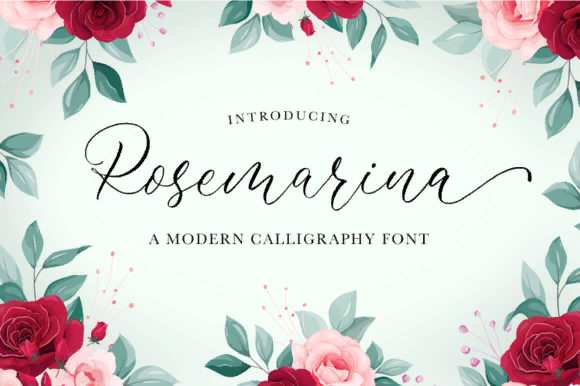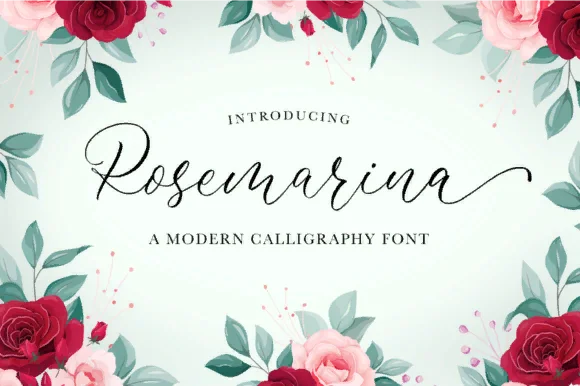
Название: Rosemarina Font (2021)
Rosemarina - это прекрасный и неподвластный времени рукописный шрифт.
Это лучший выбор для создания привлекательных логотипов, брендинга и цитат.